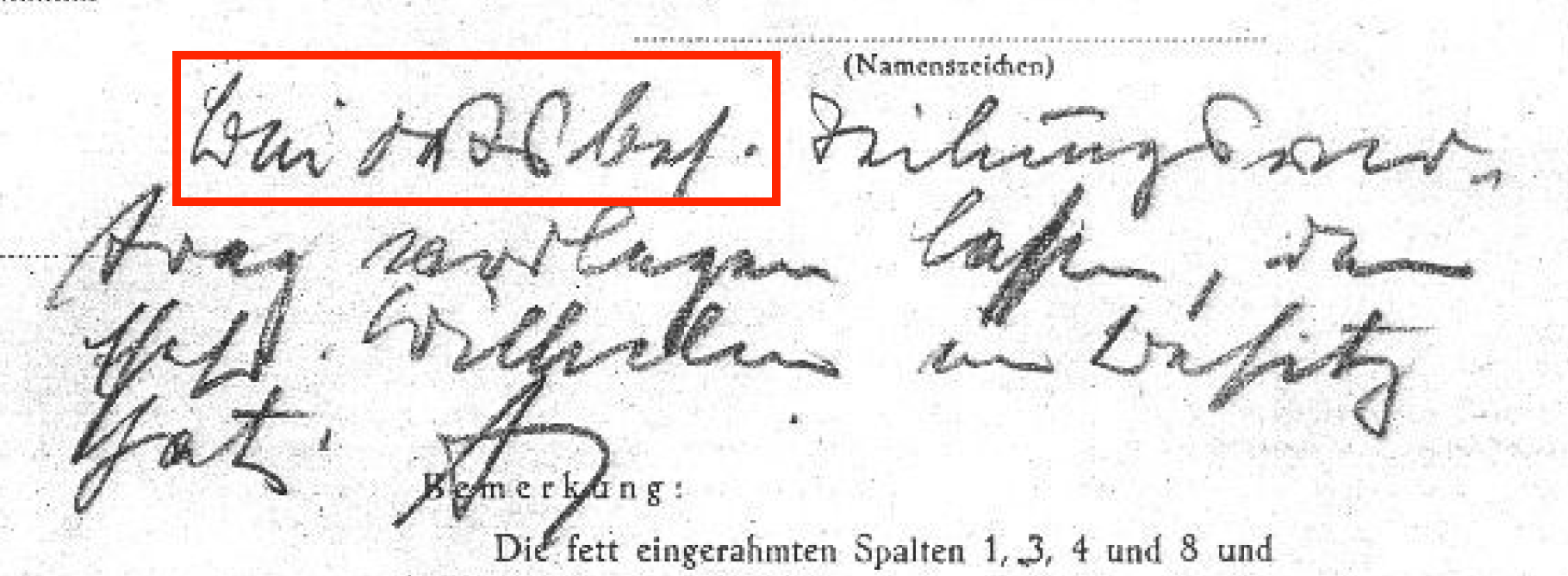
Hi, erstmal.. toll, dass es euch gibt, ich glaube ihr werdet mir sehr helfen können und dass nicht nur bei meinem erstem Problem:
Ich weiß nicht ob es Sütterlin ist, jedenfalls kann ich den rot eingerahmten Teil nicht entziffern..
Der Rest lautet (so glaube ich): "... Teilungsvertrag vorlegen lassen, den Herrn Wilhelm in Besitz hat." gefolgt von einem Namenskürzel.
Immer wenn ich im Forum vorbeischaue, habe ich einen Blick auf den unleserlichen roten Kasten geworfen, leider ohne Erfolg. Mein Ausgangspunkt war "Bei … sbes[itz]"; vor allem das Schluss-s ist ja sehr deutlich. Nur kann ich mir den Rest nicht wirklich zusammenreimen. Ich hätte auf etwas wie "Hausbesitz" o.ä. gehofft; das ist aber sehr weit vom Schriftbild entfernt. Alternativen wie "Gutsbesitz" sind ebenfalls unwahrscheinlich. Möglicherweise handelt es sich um einen Standardbegriff in dieser Art von Dokument, der deshalb abgekürzt wird.
Der einzige Punkt, bei dem ich recht sicher bin, ist das Wort "Ehefr[au]" (anstelle von "Herrn") in der dritten Zeile.
He, danke für dein Interesse.. Also der Standard Begriff wäre vielleicht Hofraum,, abgekürzt wurde dieser normalerweise HF, möglicherweise  HFR..